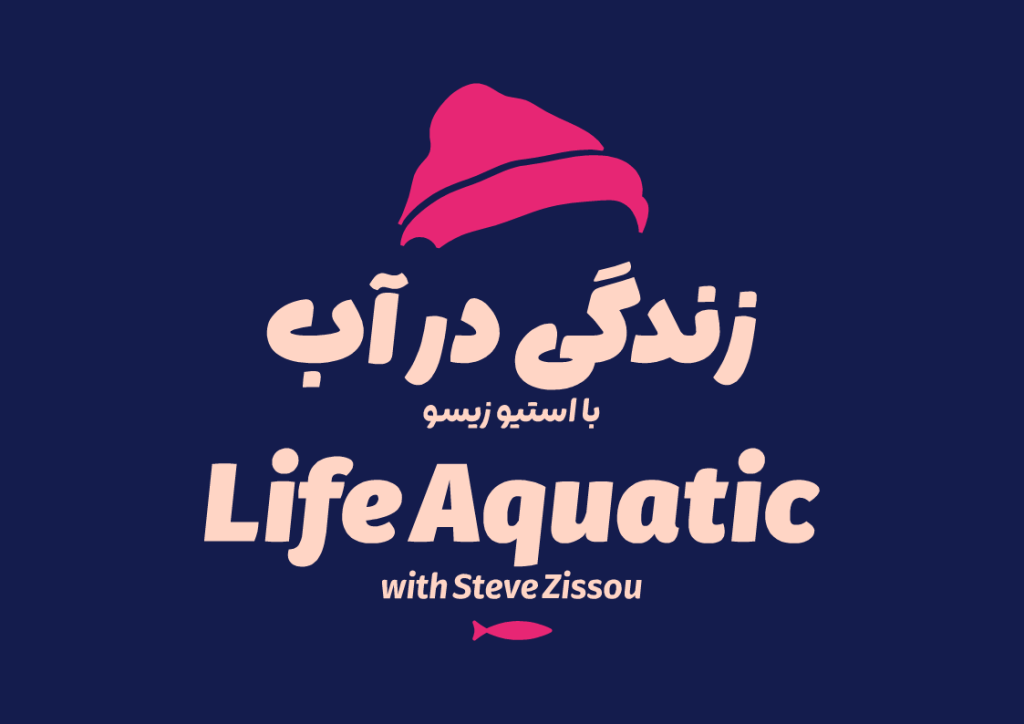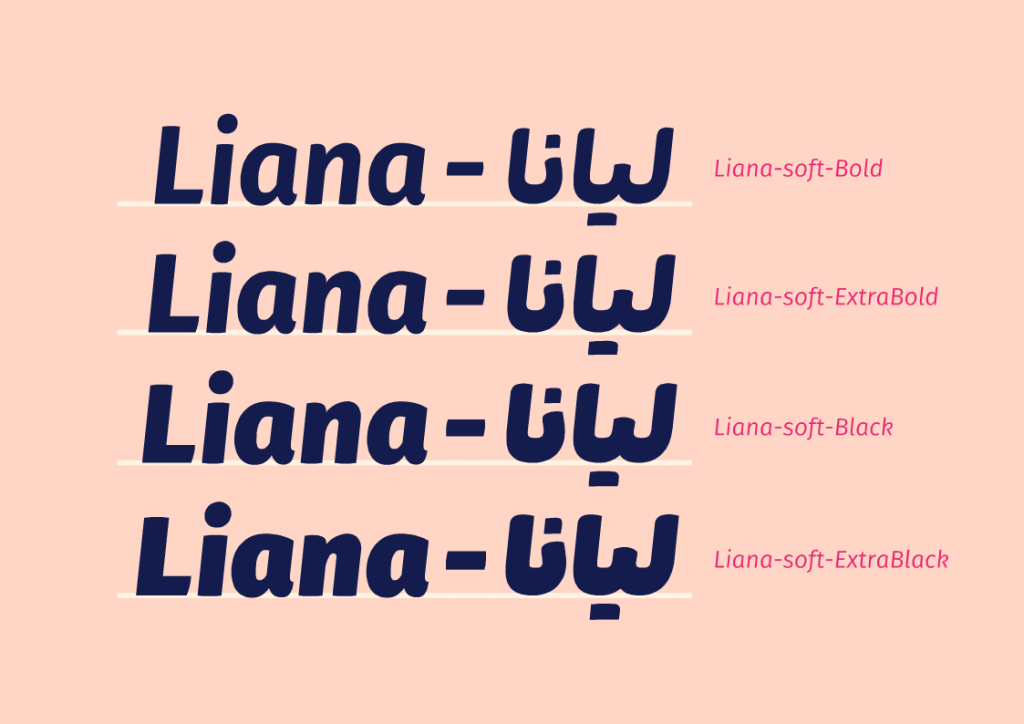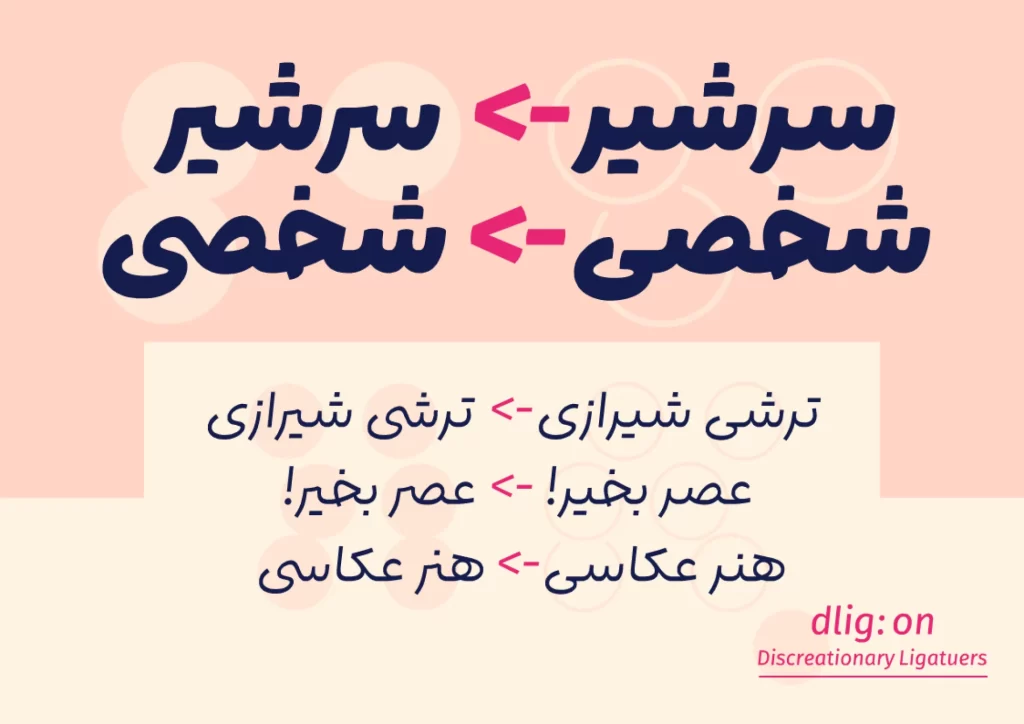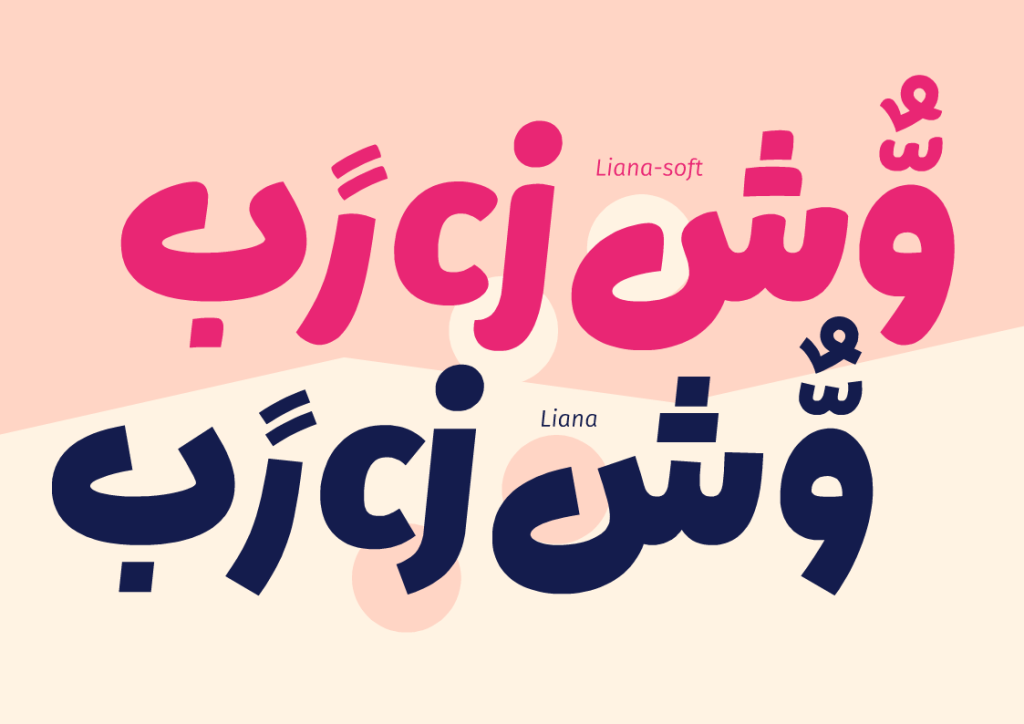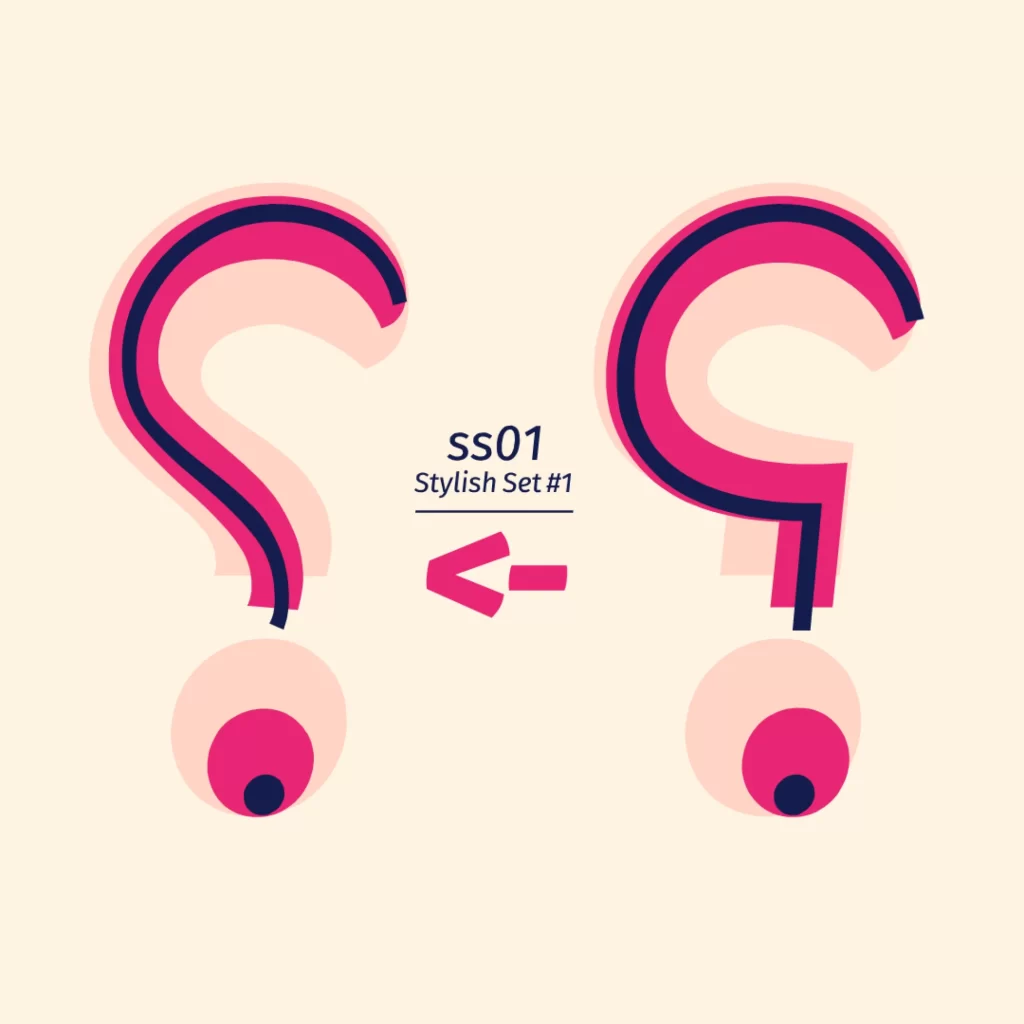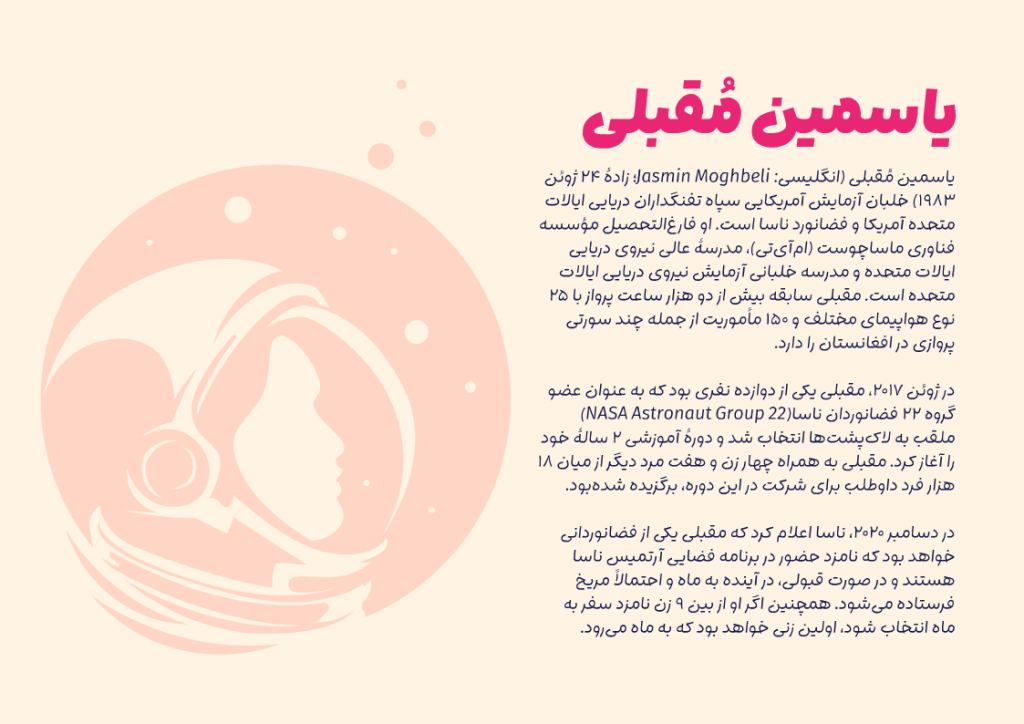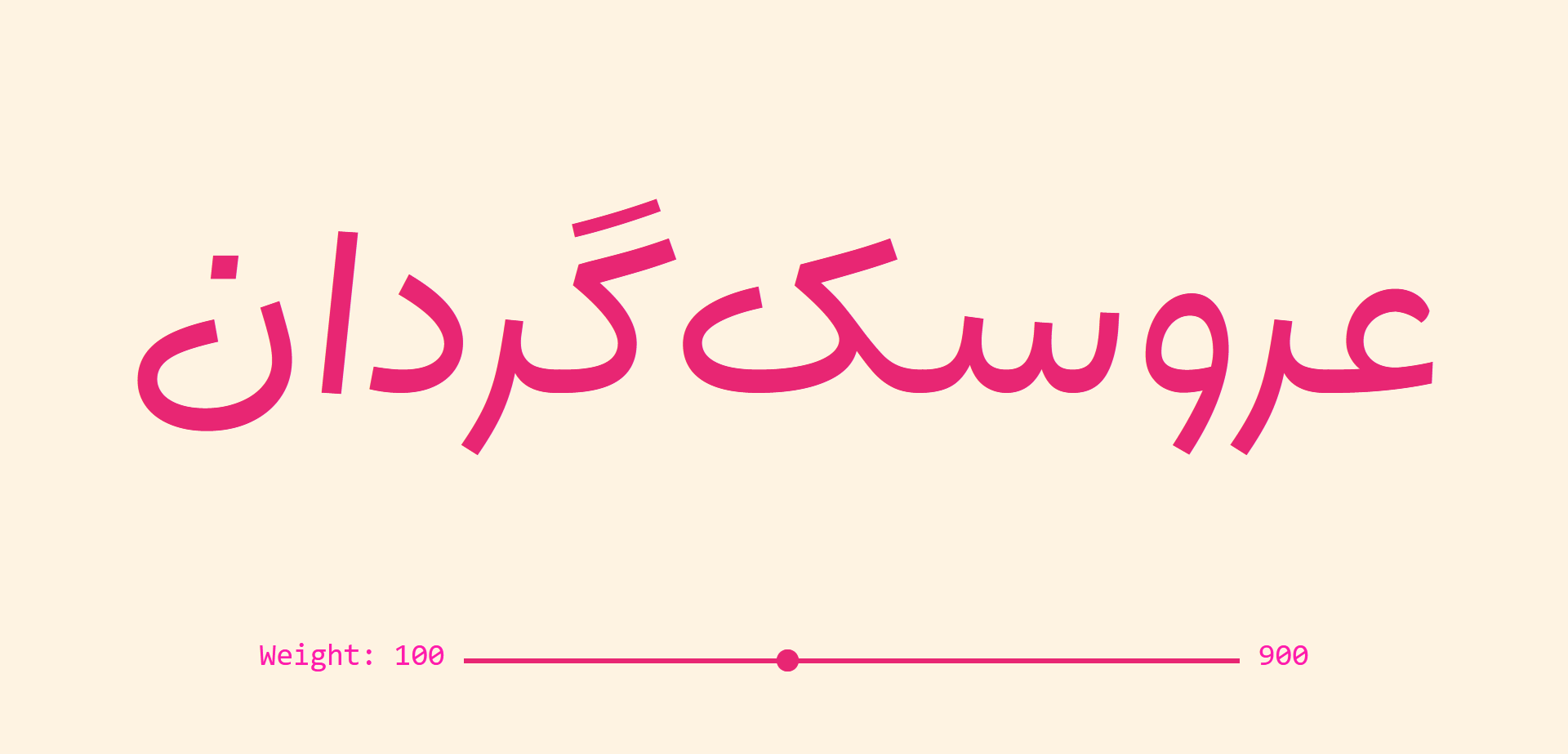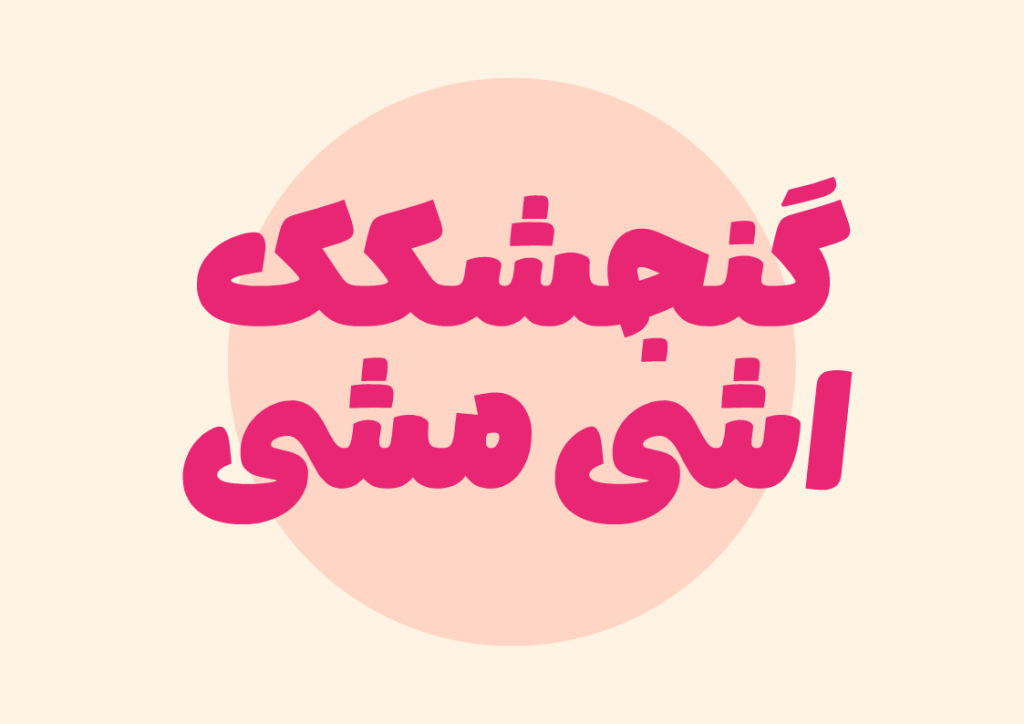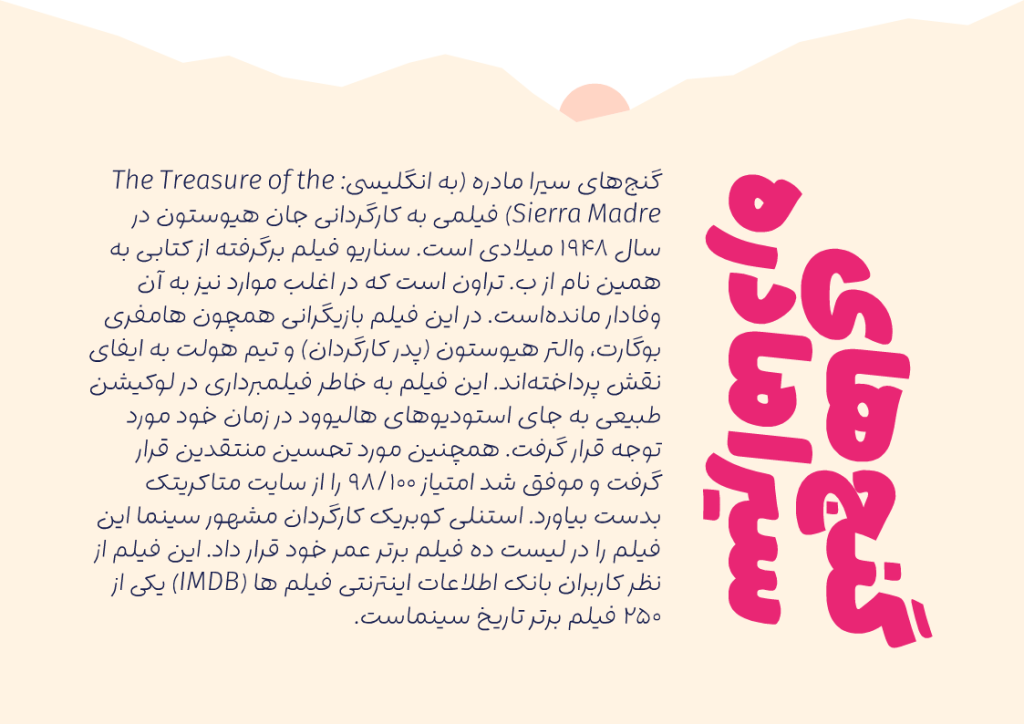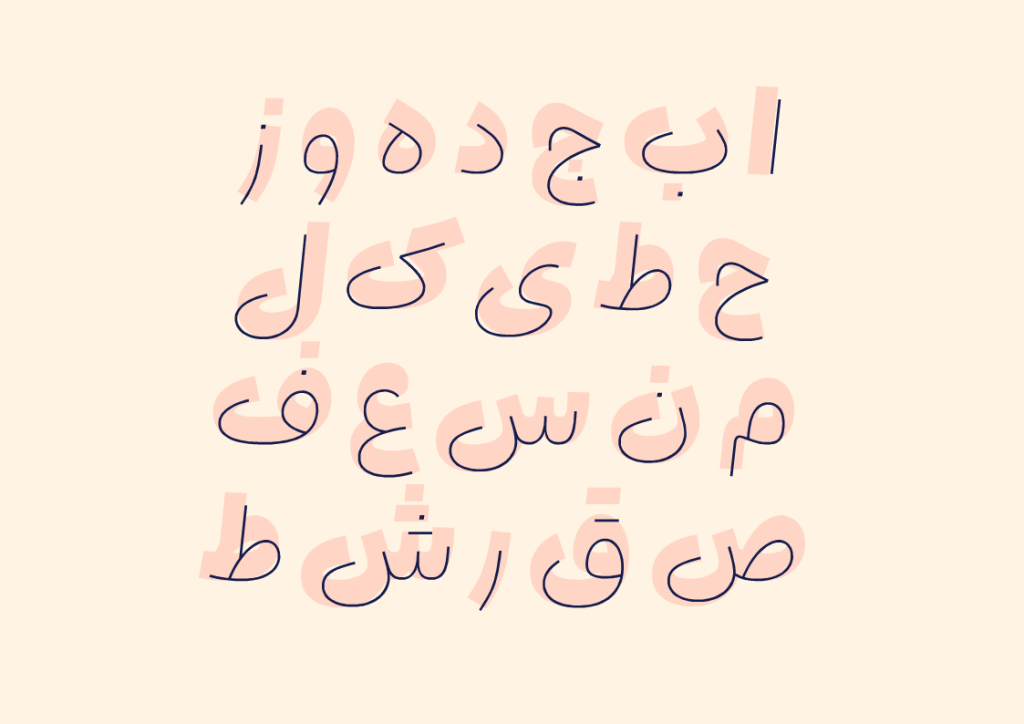
فونت لیانا قلمی دست نویس
فونت لیانا تایپ فیسی از نوع دست نویس که برگرفته شده از تایپ فیس هایی قدیمی مانند فرناز، مهر و … می باشد . از تصاویر نمونه از لیانا کاملا مشخص است که دارای جذابیت های بصری و القای حس گرم و صمیمی به خوانندگان به خود است. لیانا دارای شخصیتی پرتلاش جوان و به نوعی نمایشی است که به دنبال نگاه مخاطبان به خود می باشد.
ایران سنس دست نویس هم مانند لیانا دارای فرم های نرم و سیال می باشد و از نقطه نظر هم خانوادگی و شباهت به این قلم شباهت بسیار دارد. لیانا جهت افزایش جلوه های بصری و زیبایی و همچنین رفع خستگی چشمان مخاطبان خود دارای زاویه انحرافی حدود 6 درجه می باشد که سبب افزایش القای حس تحرک و پویای در نوشته میشود.
این قلم دارای دو سبک نوشتاری است، فونتهای اصلی (Sans) دارای ۹ وزن و سبک نرم (Soft) دارای ۴ وزن است. لینا به واسطه این دو سبک دو منظوره یا به اصطلاح دو موتوره می باشد نسخۀ سنس بیشتر برای کاربردهای بهینه شده و نسخۀ سافت برای کاربردهای نمایشی در سایز بالا است.
برای بخش لاتین این قلم از تایپفیس متنباز Fira Sans Italic همراه با کمی دخل و تصرف(مخصوصاً در نسخۀ soft) استفاده شده. در زیر می توانید تصاویری نمونه از این قلم زیبا را مشاهده کنید.
فارسی , عربی , کوردی
13 وزن + 2 سبک